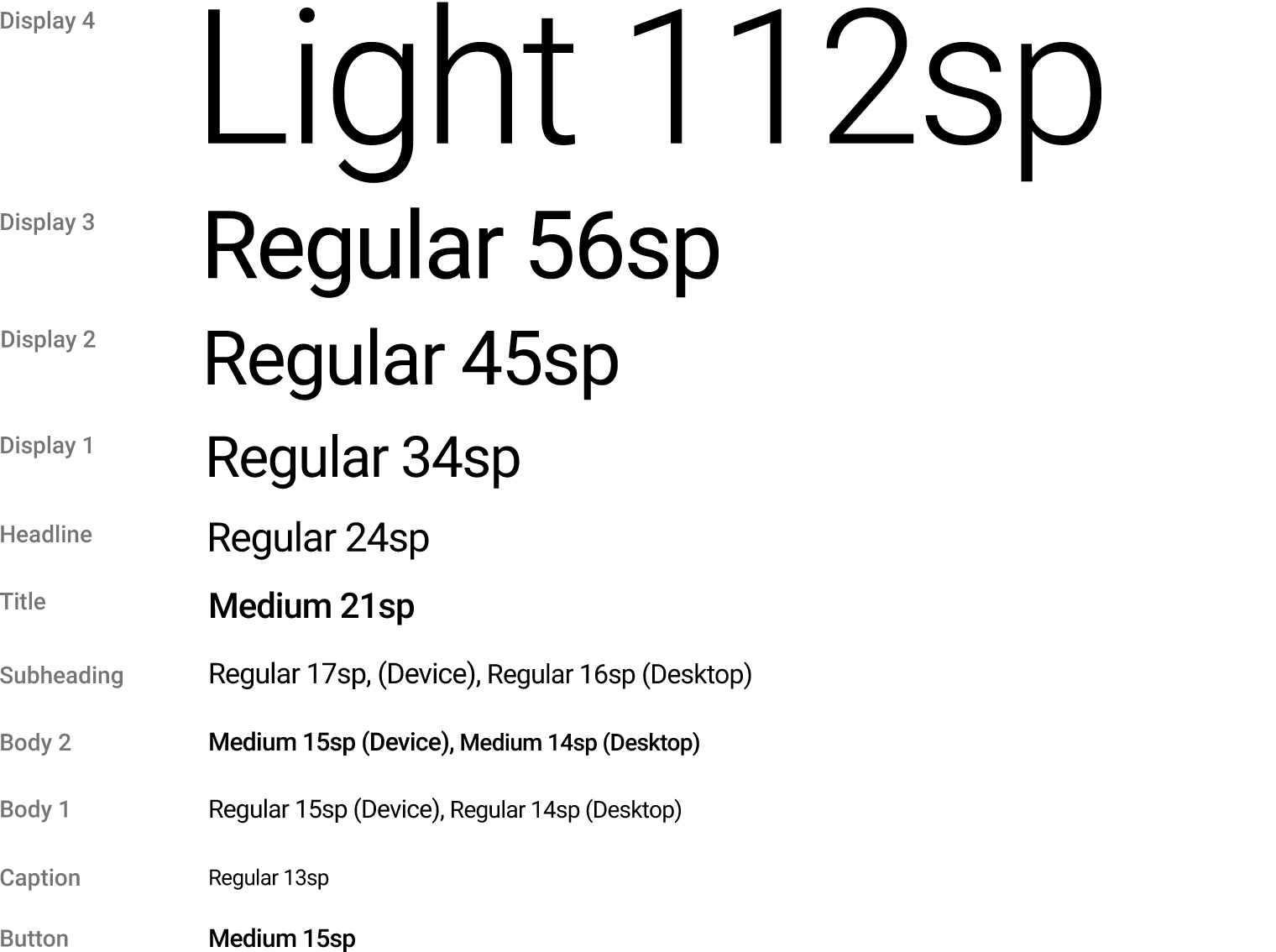
Веб-шрифты хорошо подойдут для оформления веб-сайтов, отличаются современным стилем, читаемостью и большом набором символов для различных языков.
Как правильно использовать шрифты в веб-дизайне
Никто не отрицает, что первое впечатление имеет огромное значение.
Это правило относится к различным аспектам нашей жизни, включая веб-дизайн. Не важно, являетесь ли вы брендом или занимаетесь электронной коммерцией. В любом случае ключевым моментом при посещении вашего веб-сайта являются макет и шрифт.
Почему выбор шрифта важен в веб-дизайне
Эти аспекты решают, останется ли посетитель на сайте или уйдет после первого взгляда. Поэтому, чтобы привлечь потенциальных клиентов и удержать их, необходимо всесторонне подойти к проектированию сайта.
Разработка дизайна веб-сайта — это сложная задача, требующая сочетания многих аспектов. Одним из наиболее важных является выбор типографики. В современном мире есть огромное количество шрифтов, от Google Fonts до стандартных, курсивных и других.
Правильный выбор шрифта может существенно повлиять на общее впечатление от вашего веб-сайта. Он может улучшить удобочитаемость текста, выделить заголовки и сделать контент более привлекательным для посетителей.
Если вы задаетесь вопросом, как выбрать правильный шрифт для вашего веб-сайта, то необходимо учитывать:
- цветовую схему
- макет
- навигацию и другие важные факторы.
Все эти элементы должны взаимодействовать между собой, чтобы создать гармоничный и эффектный веб-сайт.
Правильный выбор шрифта может оказать огромное влияние на восприятие вашего веб-сайта. Нужно помнить, что шрифт — это визуальный эффект, который несколько недооценивается в современном мире разработки веб-сайтов.
При выборе шрифта необходимо проявлять творческий подход и внимательно подбирать оптимальный вариант для вашего сайта.
Важность выбора лучшего шрифта для веб-сайта
Ваш шрифт — представитель вашего бренда
Имейте в виду, что у вас всего 0.5 секунды, чтобы впечатлить посетителя своим веб-сайтом и выбором шрифта. И, как показывает опыт, 94% успеха зависят от дизайна сайта.
Каждый шрифт обладает своим набором уникальных характеристик. Если вы хотите заявить о своем профессионализме, то вам крайне важно правильно подобрать шрифты и язык дизайна вашего веб-сайта.
Как улучшить пользовательский опыт
Пользовательский опыт — это совокупность впечатлений и ощущений от использования сайта или программы.
Используйте все ресурсы и внимание к деталям, чтобы создать безупречный пользовательский опыт и повысить удовлетворенность своих посетителей.
Выбор хороших шрифтов в веб-дизайне является необходимой составляющей этого процесса. Он может помочь вам привлечь больше посетителей, повысить конверсию и в конечном итоге достигнуть успеха.
Классификация шрифтов для веб-страниц
Вы знали, что каждый стиль шрифта обладает своей уникальной историей и характеристиками, что позволяет нам классифицировать их в различные группы. Существует огромное количество платных и бесплатных шрифтов, которые можно добавить на свою веб-страницу.
Для удобства, мы можем разделить шрифты веб-сайта на следующие категории:
С засечками
Примеры — Times New Roman, Garamond, MS Serif, Merriweather, Abril Fatface, Playfair Display, Georgia
Одним из старейших типов являются шрифты с засечками, которые в свое время были очень популярны за высокую читабельность.
Современные версии этих шрифтов, также известные как Serif, сохраняют историческое наследие и добавляют изящества в дизайн.
Это отличный выбор для книг и официальных веб-сайтов, где элегантность и читабельность являются ключевыми элементами.
Без засечек
Примеры — Arial, Alegreya, Open Sans, Montserrat, Comic Sans, Verdana, Oswald, Roboto, Lato, Helvetica.
7) Ubuntu (Font Squirrel, Adobe, Google)
8) Lobster (Font Squirrel, Adobe, Google)
9) Karla (Font Squirrel, Google)
10) Monserrat (Font Squirrel, Google)
11) Droid (Font Squirrel, Adobe, Google)
12) Roboto (Font Squirrel, Google)
13) Raleway (Font Squirrel, Adobe, Google)
14) Open Sans Condensed (FS, Adobe, Google)
15) Playfair Display (Font Squirrel, Google)